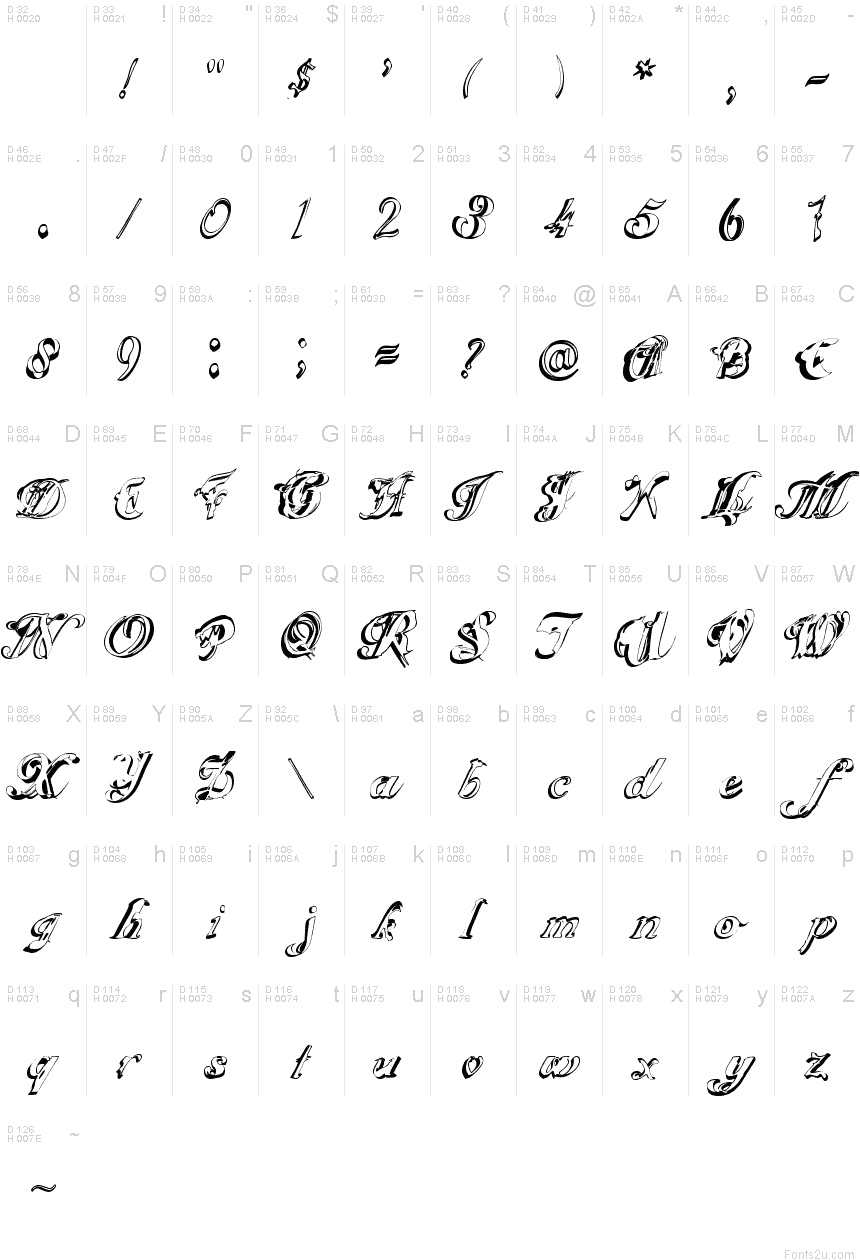
Scripteria Gummy, darmowy, gumowy font typu script od H. Patela z 1998 roku, zamienia kaligraficzne litery w coś miękkiego, napuchniętego i nieco psotnego. Znaki opierają się na zamaszystych zdobieniach, lśniącym kontraście między grubymi a cienkimi liniami oraz wydatnych krzywiznach, dzięki czemu styl wydaje się bardziej teatralny niż formalny.
Pasuje do nagłówków plakatów, opakowań butikowych, okładek magazynów retro, zabawnych szkiców logo i plansz tytułowych, gdzie kilka słów wystarczy, by nadać ton; ten darmowy krój sprawdza się zwłaszcza wtedy, gdy potrzebujesz energii pisma odręcznego bez zbyt wygładzonego charakteru zaproszeń ślubnych. Używaj go w krótkich hasłach marki, nazwach produktów lub dekoracyjnych inicjałach, ponieważ te zapętlone kreski i gumowe kontury przyciągają wzrok od razu.